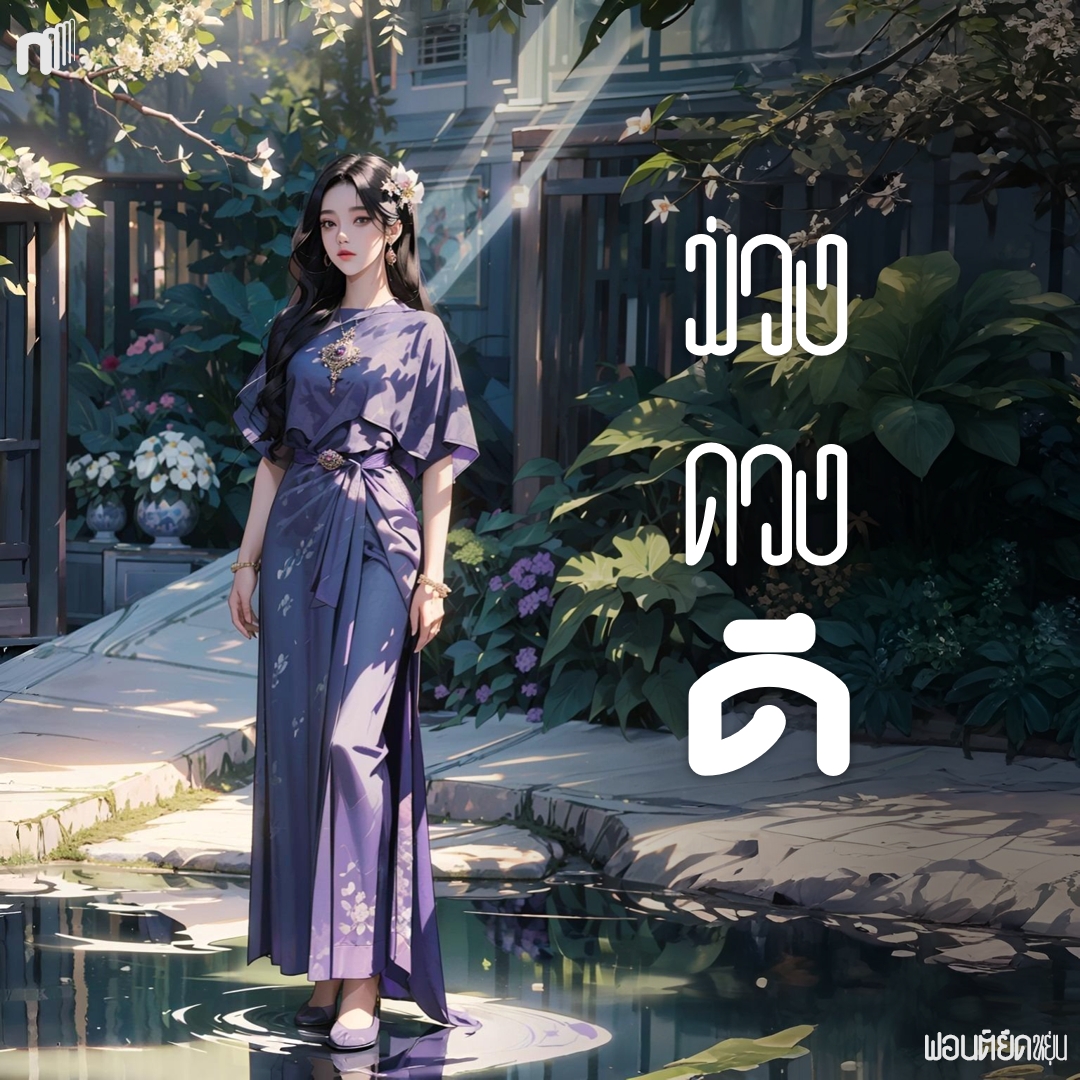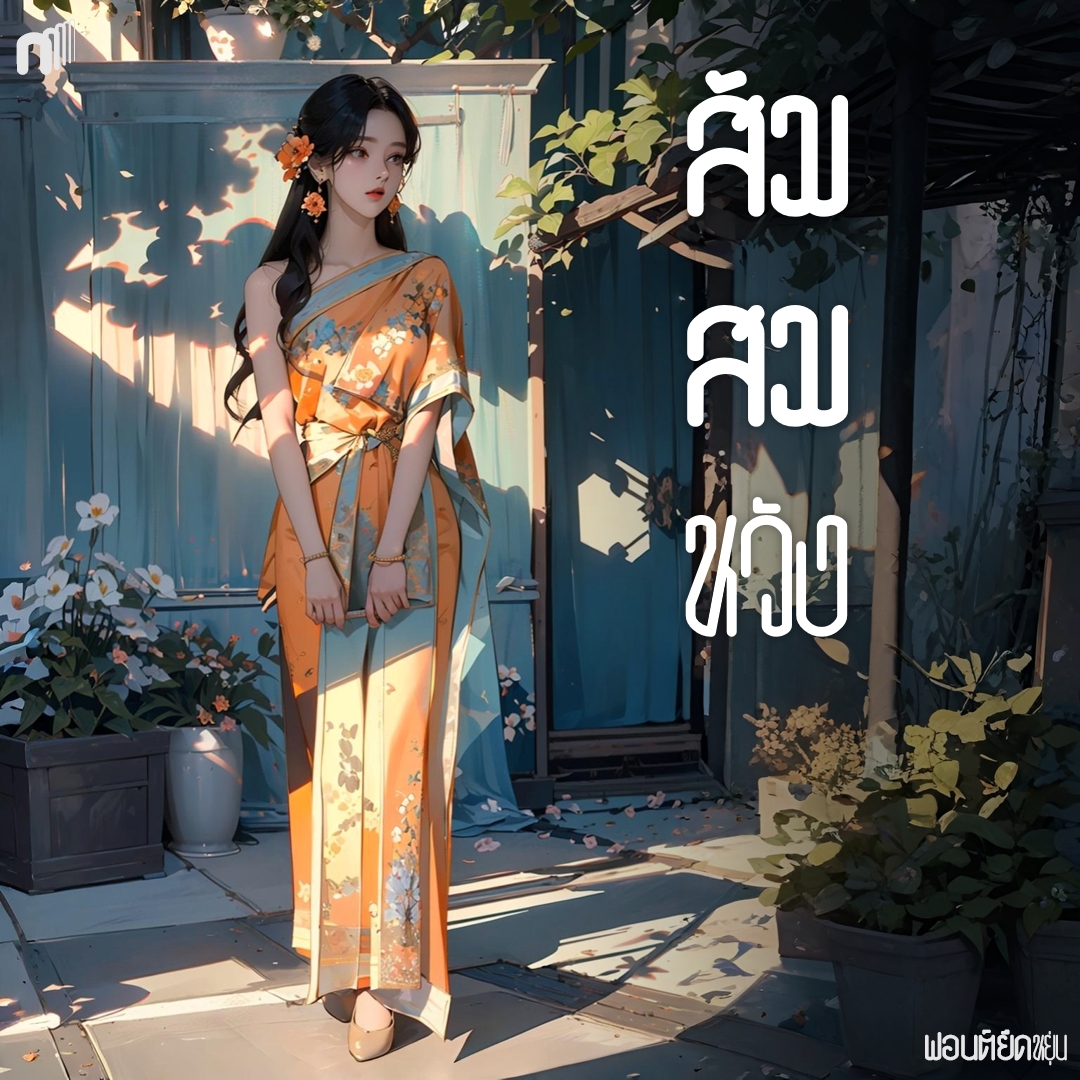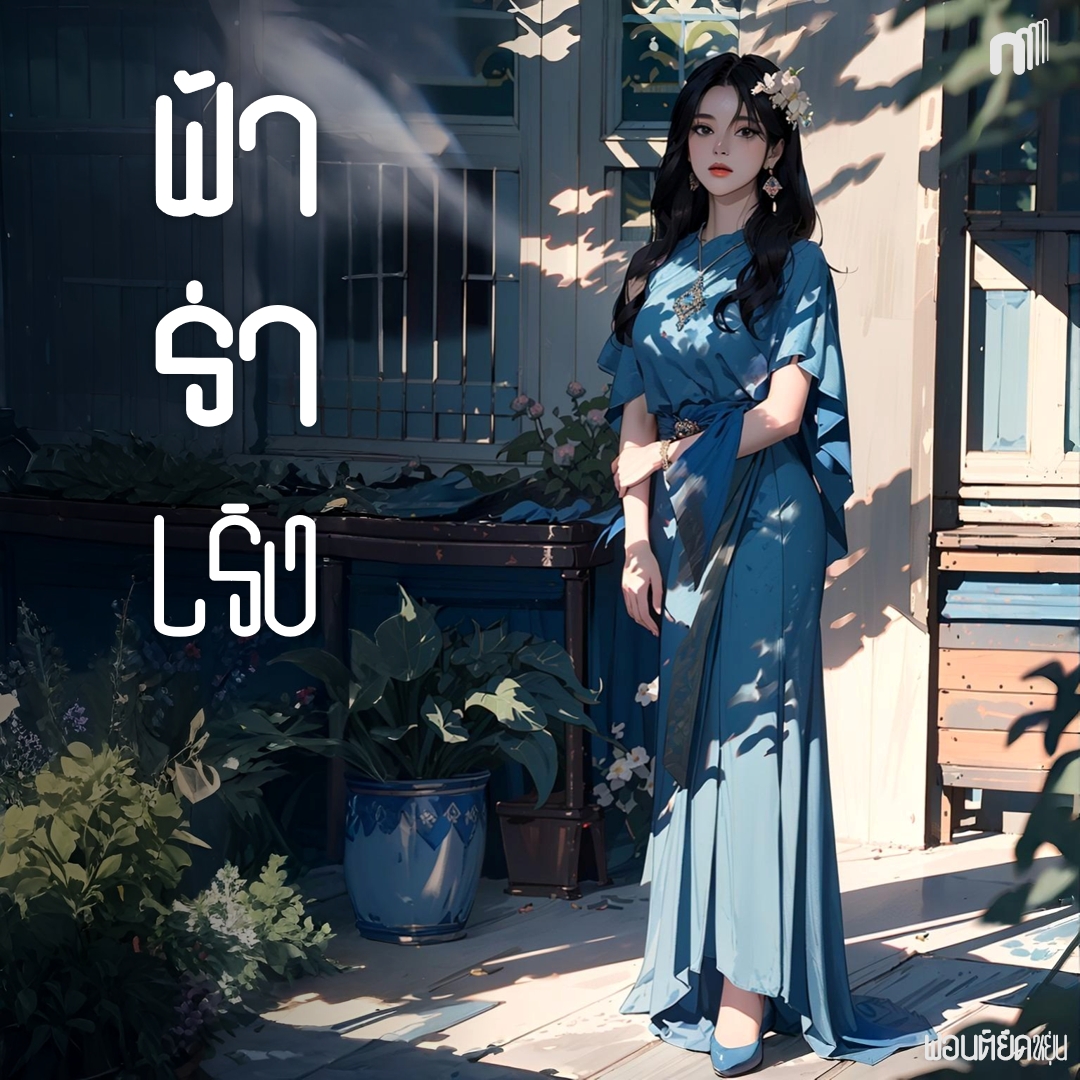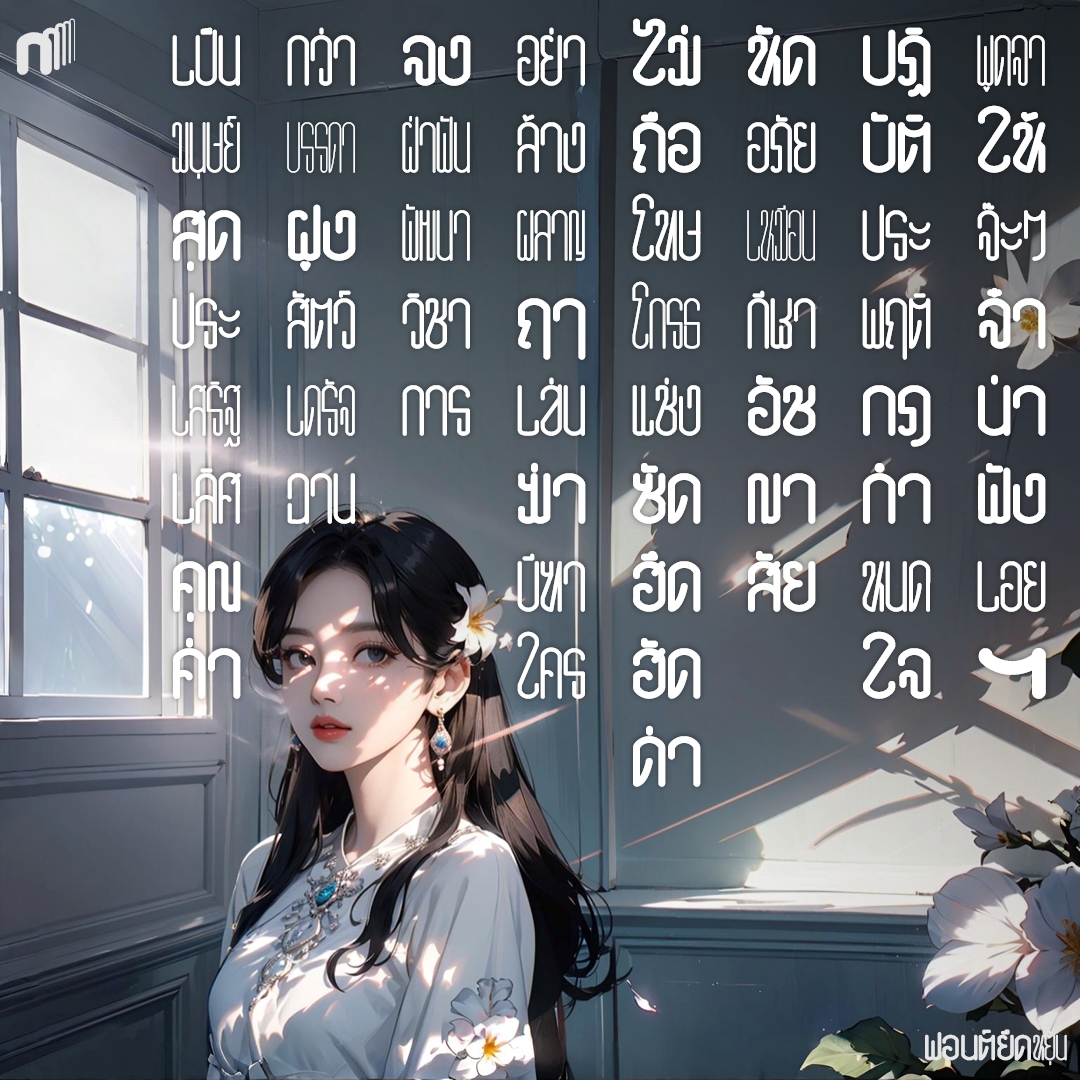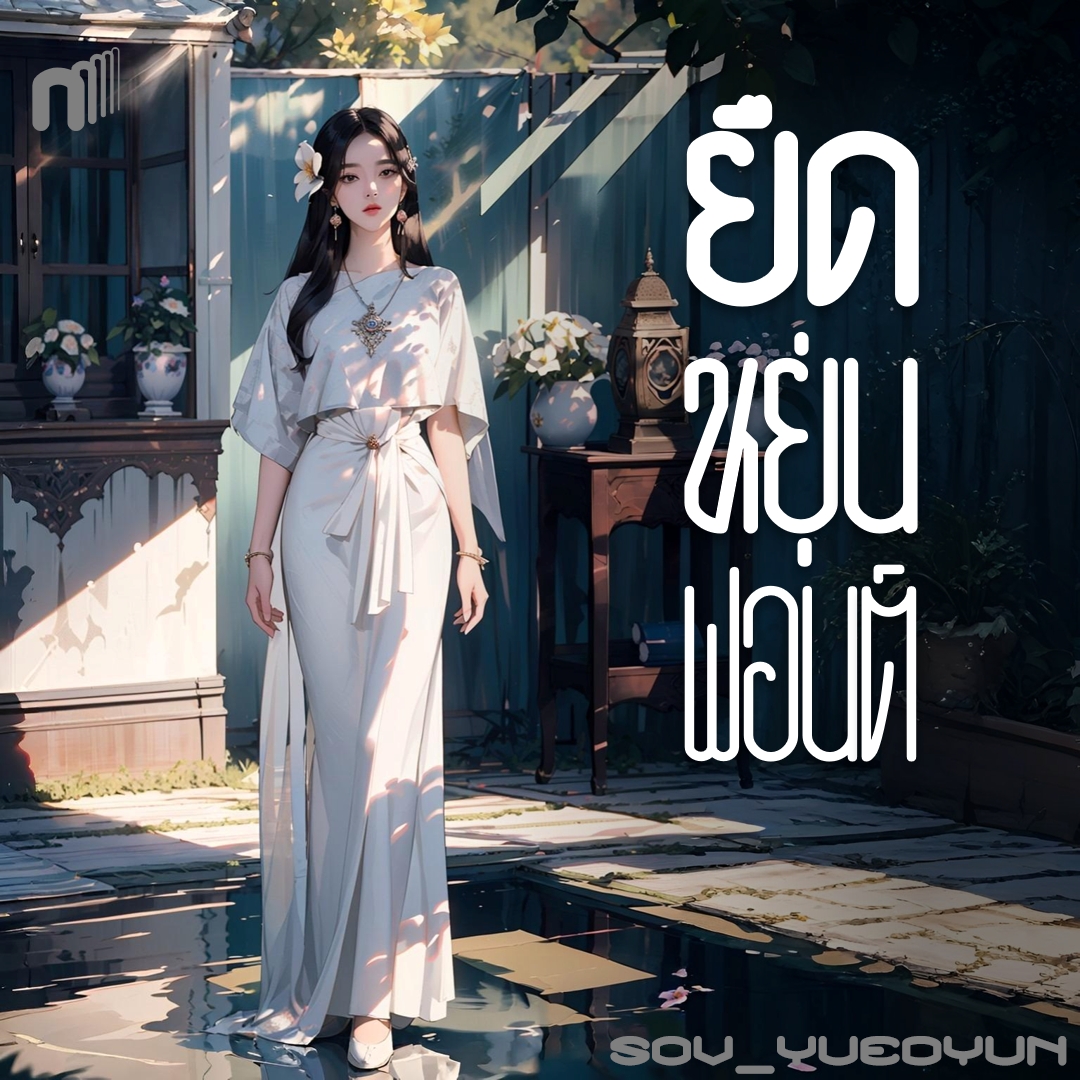
ฟอนต์ ยืดหยุ่น
ฟอนต์ยืดหยุ่น แนวคิดจาก variable font (ชื่อไทย ก็ฟอนต์ยืดหยุ่น นี่แหละ) และแนวคิด monospace หมายถึงกว้างเท่ากัน แต่เป็น 1 ตัวอักษร กว้างเท่ากับ 2, 3, 4, 5 ตัวอักษร โดยทำตัวอักษร 1 ตัว ให้หนาสุด (weight=100) กว้างสุด (width=1), พอ 2 ตัวอักษร ลดความหนา (weight=100) ความกว้างลดลง (width=1/2), ไปจนถึง 5 ตัวอักษรบางสุด (weight=10) แคบสุด (width=1/5)
ชื่อฟอนต์ : ยืดหยุ่น
ฟอนต์ยืดหยุ่น แนวคิดจาก variable font (ชื่อไทย ก็ฟอนต์ยืดหยุ่น นี่แหละ) และแนวคิด monospace หมายถึงกว้างเท่ากัน แต่เป็น 1 ตัวอักษร กว้างเท่ากับ 2, 3, 4, 5 ตัวอักษร โดยทำตัวอักษร 1 ตัว ให้หนาสุด (weight=100) กว้างสุด (width=1), พอ 2 ตัวอักษร ลดความหนา (weight=100) ความกว้างลดลง (width=1/2), ไปจนถึง 5 ตัวอักษรบางสุด (weight=10) แคบสุด (width=1/5)